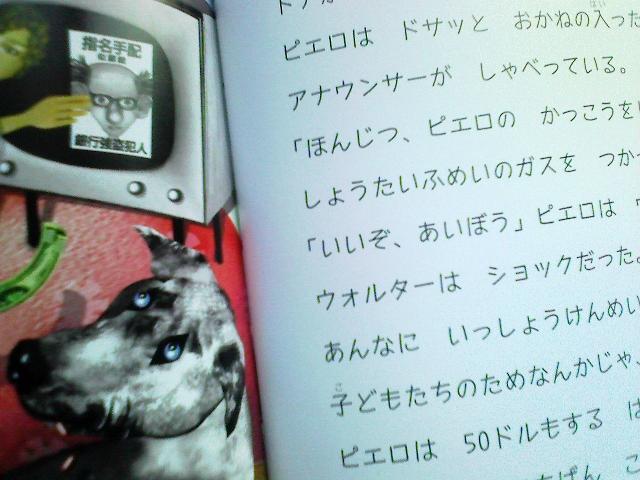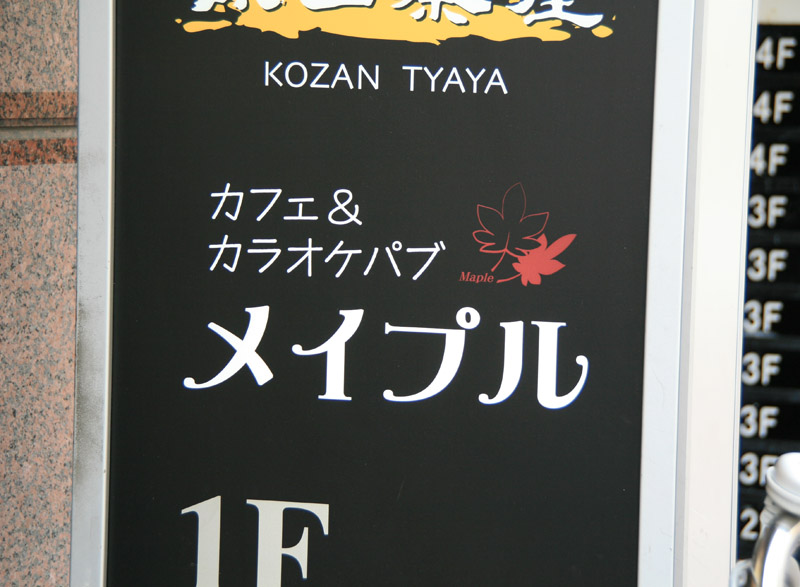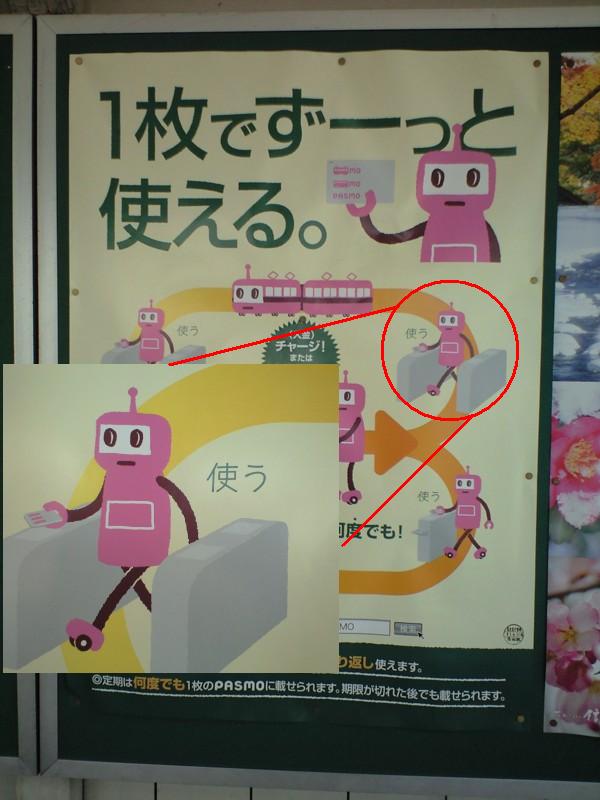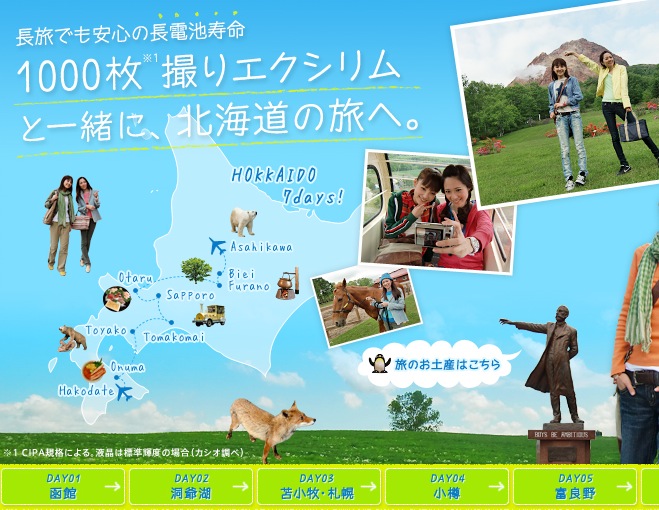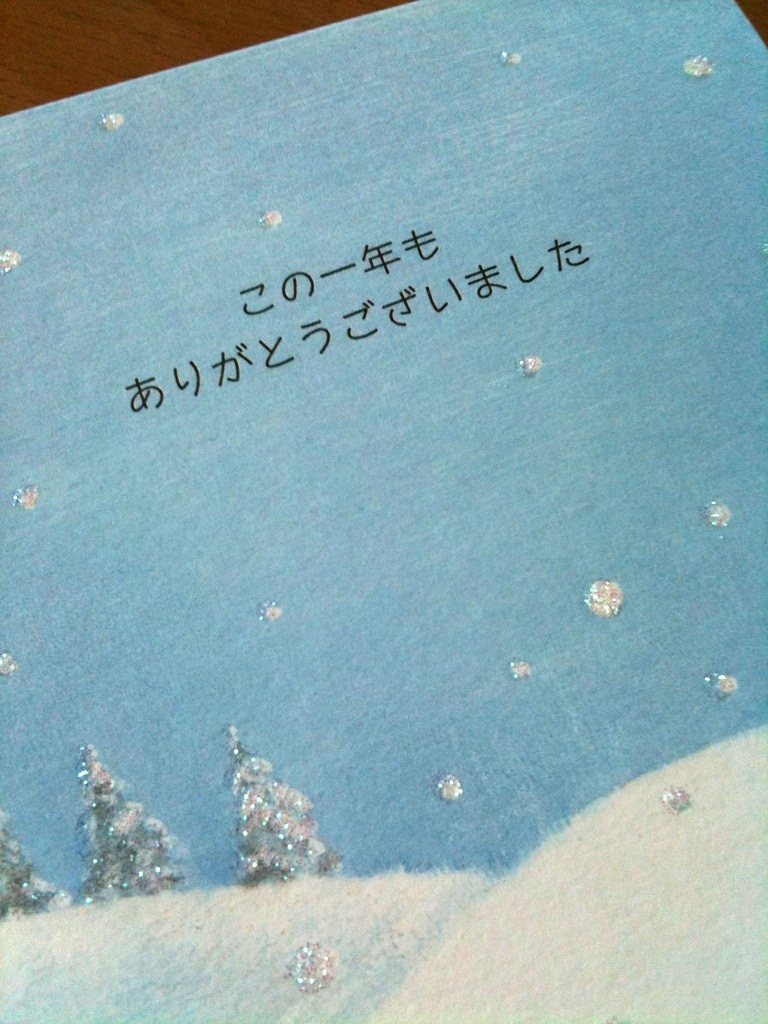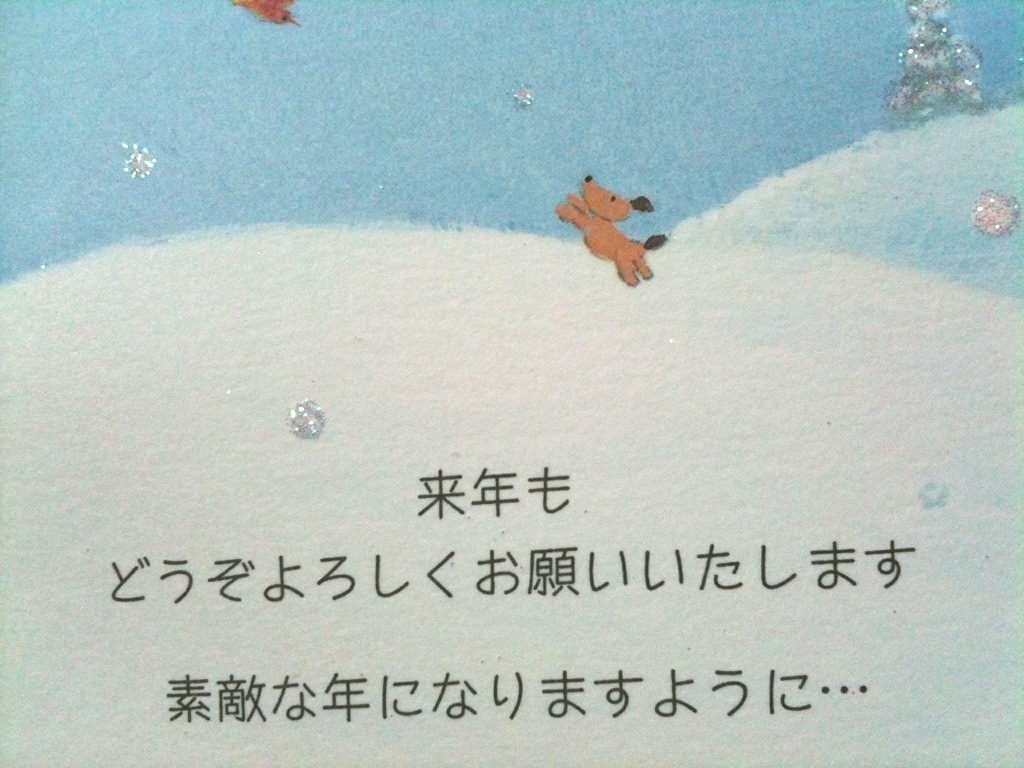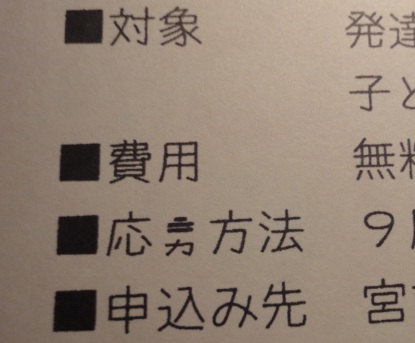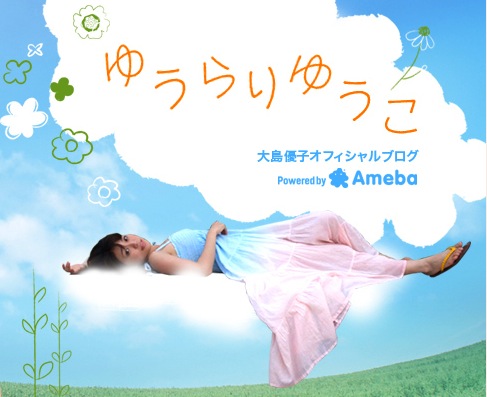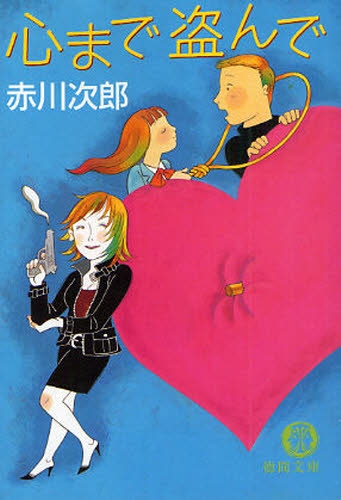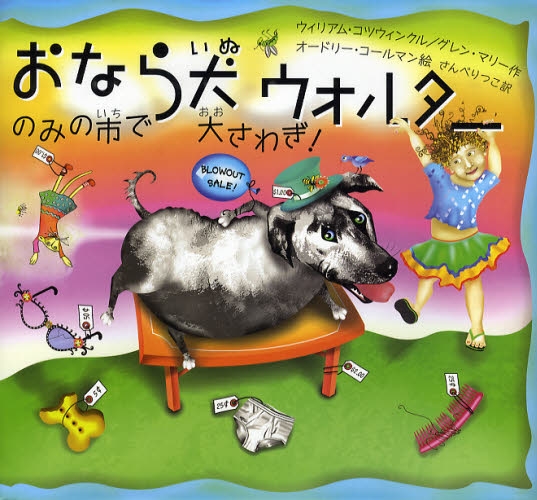
コーベアーオフィシャルサイト  はつ子  2011年6月6日(月) 21:58
はじめまして。以前セプテンバーやアニト等のフォントを購入した者です。
神戸のキャラクター、コーベアーのサイトでセプテンバーが使われているのを発見したのでご報告します。
↑ストーリーの文章が全部セプテンバーです
絵本のような雰囲気にぴったりでした
↓ここですね。
←こんな感じで使ってくれています。
グラビアページ  さとうゆたか  2011年5月23日(月) 8:01
ビッグコミック・スピリッツという週刊漫画雑誌の巻頭ページ。
先週発売された号。
催し物のタイトル  さとうゆたか  2011年5月6日(金) 10:12
北千住の丸井地下で、現在開催中。
やはり、もう少し太めのものが必要だな…。
今朝の読売新聞。
スカパーのカラー全面広告。
Mウェイトを少し太らせてあるようだ。
こちらが全面の画像。
最下段にも使われている。
本の表紙  さとうゆたか  2010年9月24日(金) 10:56
書名:なんにもうまくいかないわ
著者:平安寿子
発行:徳間文庫
こんばんは♪♪セプテンバーのフォントはめっちゃお気に入りで…、すべてのものに使わせて頂いています。いろいろなご本に使用されているのを、今ここに来て知りました。すごいですね〜〜。ところで、びっくりしたのでお知らせします。NHK海外ドラマ「新ビバリーヒルズ青春白書」のHPに行ってみた事がありますか?これはゼッタイ!セプテンバーのフォントですよね♪♪それがお知らせしたくって〜!ちょっと見てみてくださいなぁ〜!ご存知だったら…ゴメンナサイ(^_^)/ http://www9.nhk.or.jp/kaigai/90210/
「新ビバリーヒルズ青春白書」のサイト、見ました。
まったく知りませんでしたよ、セプテンバー書体、大活躍ですね。
多くの人に愛されて幸せな書体なんだ…と思います。
こんにちは。
岩塚製菓「えびカリ」という商品パッケージの、
外袋・内袋それぞれの裏面にセプテンバーを見かけました。
海老とカレーを組み合わせた「えびカリ」、美味しそうですね。
見出し部分に  さとうゆたか  2010年8月26日(木) 13:49
本文ページ左側の見出し部分を抜粋。
書名:せいかつの図鑑
著者:流田直
発行:小学館
AKB大島  さとうゆたか  2010年7月22日(木) 8:29
ブログのトップページに使われています。
印刷すると「募」が半分消えます。  miao-miao  2010年7月12日(月) 23:06  HP
いつも嬉しい気持ちで使っています。
セプテンバーLの正規版です。
パソコンの画面上は問題なく表示されています。
他の文字は問題なく印刷できるのですが、何故か「募」だけ印刷されているところと印刷されていないところができます。
アウトライン化すれば印刷可能ですが、よく使う文字なので解決できたら・・・・と思い、おじゃましました。よろしくお願いします。
OS9で作成したPDFを、OSXからプリントしてるんですね…。
そして、プリントするAdobe Readerも最新のものを使ってはいないのですね…。
対策方法は、ちょっとわかりません…。
このフォントは、とてもデータ量が大きいので、パソコンやアプリやプリンタのメモリが足りないとき、不具合が出ることがあるかもしれません(ユーザーから報告があったわけではないです)。
本当はイラレの最新版にすればいいのですが、なかなかそうもいかなくて。
アウトライン化で対応します。
また、解決したらご報告しますね。